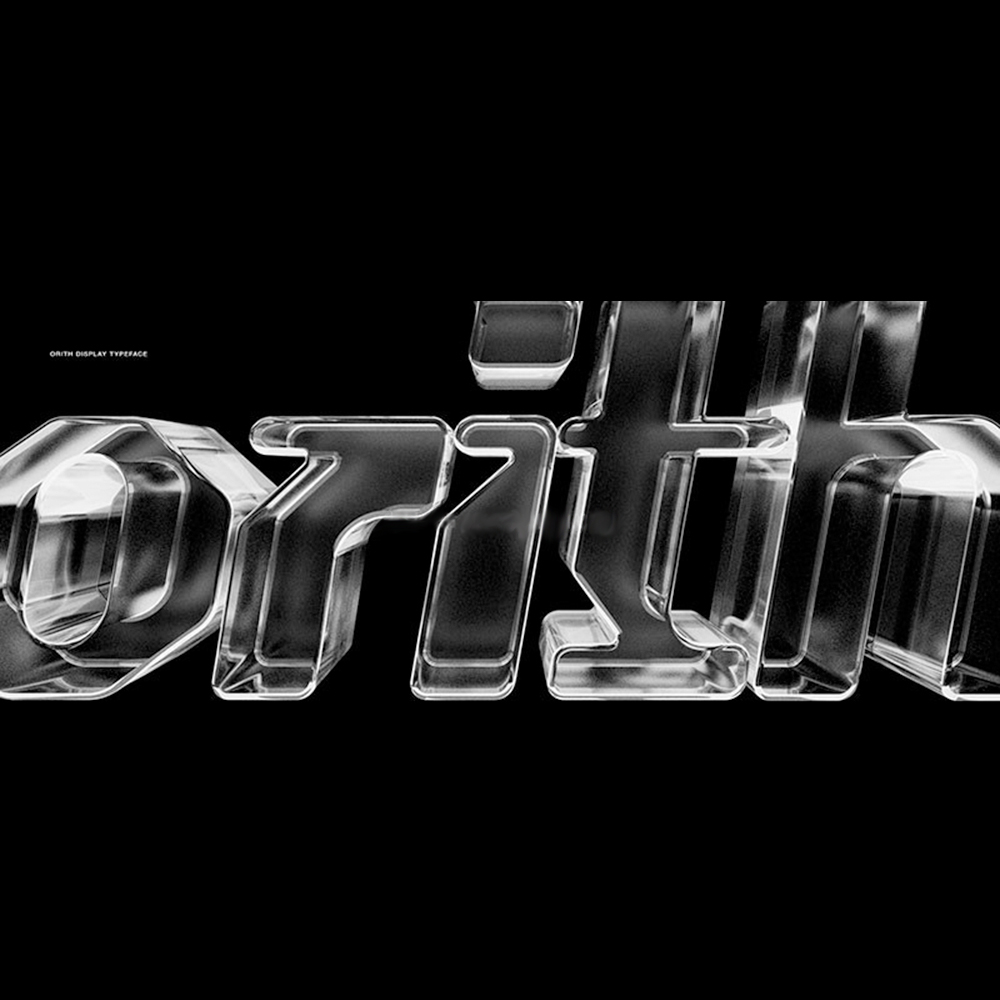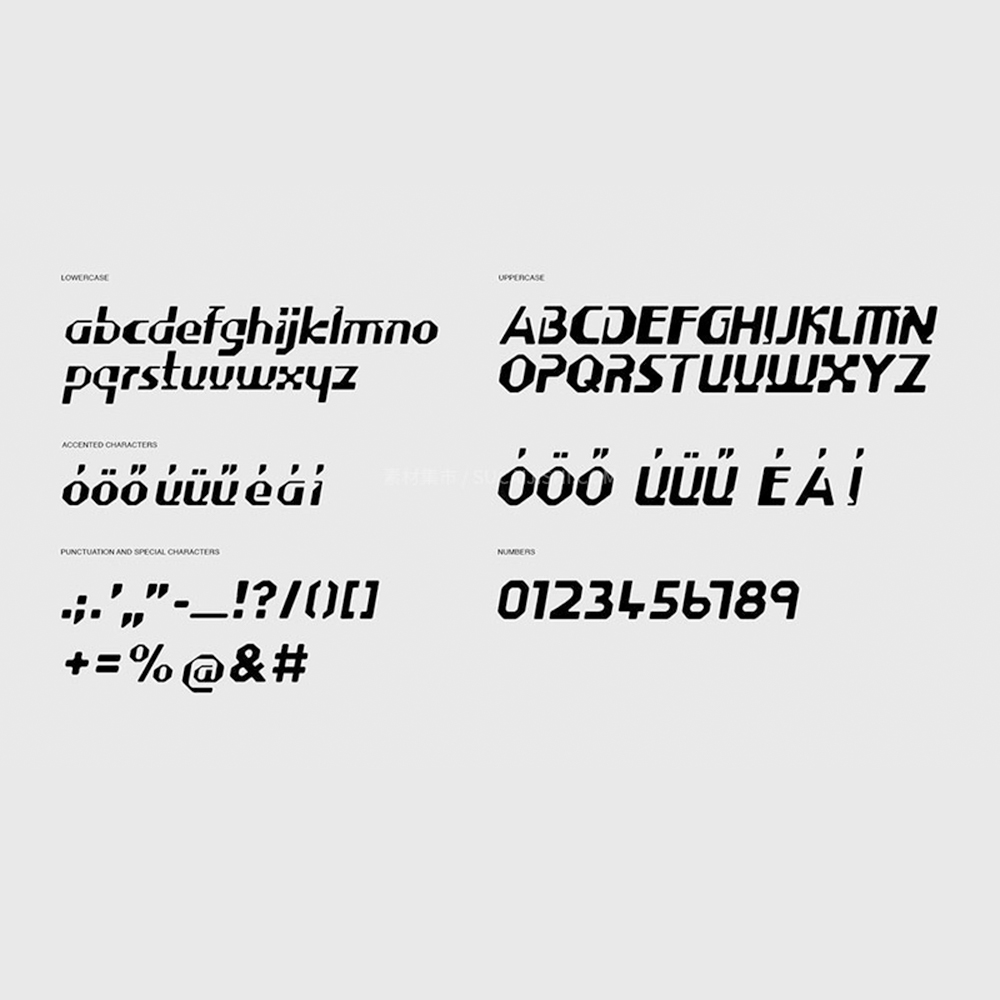
دانلود فونت انگلیسی Orith Display Font
فونت پرمیوم و انگلیسی Orith Display Font یک فونت نمایشی است که روح بازیهای مسابقهای دهه ۲۰۰۰ را القا میکند. طراحی کمی کج و لبه تیز آن، حس سرعت بالا و تیزی را القا میکند. مدرنیته آن دوران، این فونت را برای بسیاری از سبکهای زیباییشناسی، چه قدیمی و چه آیندهنگر، مناسب میکند. فونت Orith Display برای تیترها، نکات برجسته مجلات، کتابها، پوسترها، مطالب تبلیغاتی، تبلیغات، برندسازی یا هر متنی که نیاز به تقویت شخصیت دارد، مناسب است.